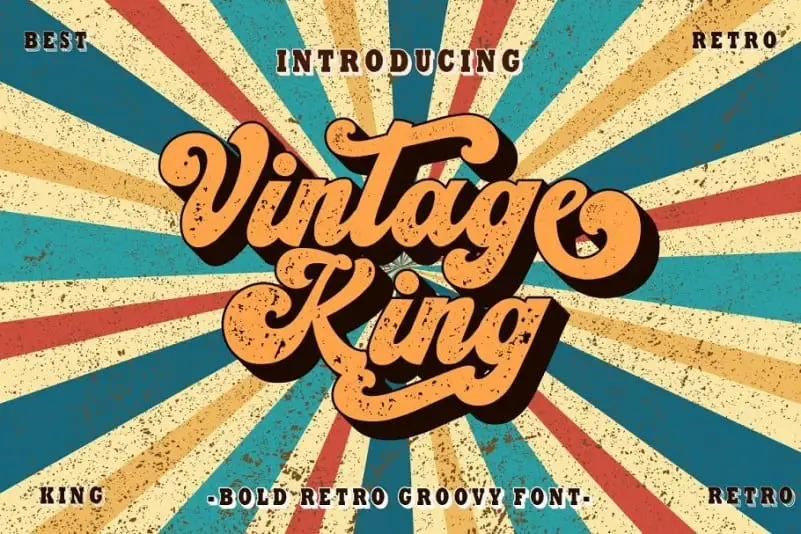
Introduzimos Vintage King Script Font, uma família de tipo stylizado com forte impacto visual que é tanto chamativa quanto assertiva. Ideal para ambientes de design onde a legibilidade precisa estar sempre presente, seja no tamanho de exibição ou texto. Feita pelo font designer PutraCetol Studio, esta fonte retrata um estilo bold e script de retro. Conforme inspirada nos estilos tipográficos de gabinetes da década de 70 e 80, Vintage King Script oferece uma versão clara e também rugosa, proporcionando diversidade nas aplicações do tipo. Através desta fonte, você pode criar elementos que remetem ao passado sem perder a relevância moderna, tornando-a ideal para design gráfico de alta qualidade. Suas características bold e script combinam perfeitamente para dar um toque especial às suas criações. Ideal tanto para projetos profissionais quanto para iniciantes em design, Vintage King Script é uma escolha confiável se você deseja incorporar estilos retro ao seu trabalho gráfico moderno.